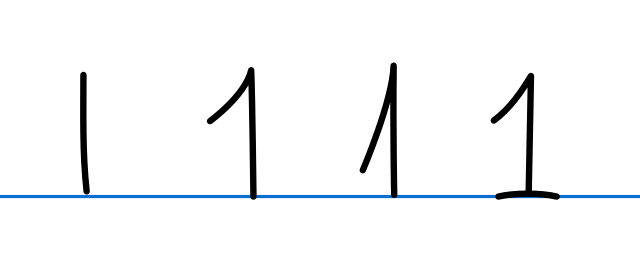
Ziffer Sieben mit querstrich
Welche Schriftart hat - wie zum Beispiel die "Baltica" einen Querstrich in der Ziffer 7?
Neben solchen Schriften mit handschriftlicher Anmutung (von denen sicher viele solche 7 haben) fallen mir als erstes Schul- bzw. Leselernschriften ein, die solche 7 haben dürften. Und gebrochene Schriften haben auffallend oft solche 7.
Hier gibt es einen Überblick der 7-Ausführung populärer freier Schriften.
Wenn wir im deutschen Sprachraum in der Schule die 7 mit Querstrich lernen, warum gibt es dann so wenige Druckschriften damit?
Weil Druckschriften gewöhnlich darauf achten, 1 und 7 ausreichend optisch zu differenzieren.
Phoibos das Argument leuchtet mir noch nicht ganz ein: Würde denn der vorhandene Querstrich eine weniger ausreichende Differenzierung zur 1 bedeuten oder wie meinst Du das?
Ich vermute Phoibos meint, dass die Unterscheidung zwischen 1 und 7 bei Druckschriften groß genug ist – auch ohne den Querstrich. Und im Sinne des Minimalismus ist es ja nur konsequent, wegzulassen, was man nicht braucht.
In Südafrika habe ich übrigens gesehen, dass viele Leute bei handgeschriebenen Ziffern keinen Querstrich bei der 7 machen, sondern stattdessen der 1 noch einen Strich auf der Grundlinie dazugeben, quasi eine breite Serife. Ich weiß aber nicht, ob die Kinder das da so in der Schule lernen. Muss ich mal fragen.
Die Serife zu positionieren erfordert eine höhere motorische Leistung als einen Querstrich zu positionieren, weil die Serife im Gegensatz zum Querstrich keinen Spielraum in Bezug auf die Position erlaubt. Insofern macht es mehr Sinn, der Verwechslungsgefahr mit einem Querstrich vorzubeugen. Frutiger geht in seinem Buch Der Mensch und seine Zeichen ausführlich auf den Zusammenhang zwischen Eindeutigkeit der Zeichen und Schwierigkeitsgrad der Schreibbewegung ein.
Mit einem Font lässt sich eine Zeichenform beliebig oft mit annähernd der gleichen Präzision darstellen. Den wenigsten Menschen gelingt es aber, dieselbe Zeichenform handschriftlich exakt zu wiederholen. Sobald der mit dem Schrägstrich verbundene horizontale Strich der Ziffer „7” hängt, besteht Verwechslungsgefahr mit der Ziffer „1”. Wenn benachbarte Ziffern keinen Orientierungspunkt in Bezug auf die Senkrechte bieten, steigt die Verwechslungsgefahr noch. Bei den meisten Druckschriften gibt es außer der Grundform eines Zeichens noch weitere Merkmale, die die Unterscheidung von anderen Zeichen erleichtern,  w. z. B. Variationen der Strichstärke, Serifen, Abweichungen von der Geraden. D. h. die Ziffer „7” einer Druckschrift ist auch dann erkennbar, wenn sie das einzige dargestellte Zeichen ist. Eine handschriftliche Ziffer „7” ohne Querstrich ist nicht ohne Weiteres als „7” erkennbar, wenn sie alleine steht. Das hängt halt von der Handschrift des Schreibenden ab, seinen  feinmotorischen Fähigkeiten u. s. w.
Es ist wie bei dem Fragezeichen. Warum ist es in Handschriften im Wesentlichen ein gespiegeltes „S”? Weil Menschen in Bezug auf die Wiederholbarkeit von Bewegungen nicht so feinmotorisch sind wie Präzionsmaschinen, eine Tagesform haben, unterzuckert sind, bewegungshemmende Kälte verspüren u. s. w. Außerdem entsteht eine Handschrift durch einen sich bewegenden Punkt, nämlich die Spitze des Schreibwerkzeugs. Ein Zeichen einer Druckschrift wird hingegen mehr oder weniger als Ganzes zu Papier oder auf den Bildschirm gebracht. D. h. der Computer beginnt schon damit das zweite Zeichen in einer Zeile darzustellen, während er noch mit der Darstellung des ersten Zeichens beschäftigt ist.
Ist hier ?‍? ja so ähnlich. Werden nur Ziffern geschrieben (Telefonnummern, Preise, …) ist die 1 nur ein senkrechter Strich (Variante ganz links). Drohen in gemischt alphanumerischem Text Verwechslungen mit I oder l, kann die 1 mit kleinem (!) Anstrich und mindestens ebenso langer Grundlinienserife geschrieben werden (Variante ganz rechts).
Die Varianten in der Mitte wäre in Amerika falsch, da zu ähnlich der 7, die ohne Mittelquerstrich geschrieben wird.
Handschriftlich Post von hier nach Deutschland zu adressieren, ist deshalb problematisch. Deutsche Einsen würden von amerikanischen Postlern und -lesegeräten als 7 gelesen; amerikanische Einsen der schlichten Variante würden in Deutschland nicht richtig interpretiert. Und umgekehrt ist das auch so. Wir bekommen regelmäßig verzögerte Post aus Deutschland, die mit gestempelten und handschriftlichen Irrläuferbehandlungsnotizen übersät ist, die verraten, dass die Post erst mal nach Texas (Postleitzahlbereich 7) geschickt wurde statt gleich zu uns  in den Nordosten (Postleitzahlbereich 1).